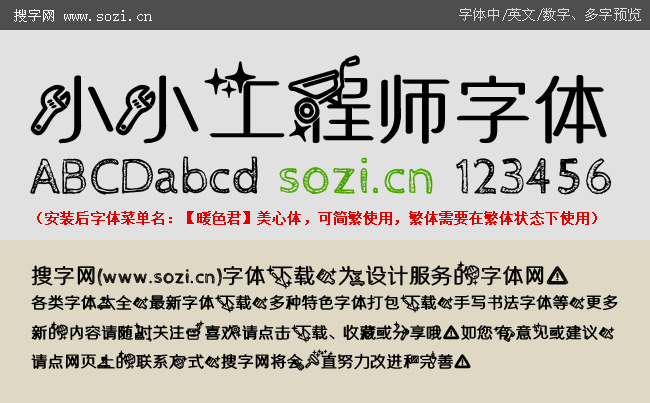
小小工程師字體
搜字網(wǎng)給大家提供一款小小工程師字體手機(jī)中文字體下載。這款手機(jī)字體是以圓體字體為原形,筆畫間嵌入了可愛的卡通工具圖案。在具備圓字體清晰端正的風(fēng)格同時,卡通味也特別濃,是一款非常可愛的卡通字體,特別適合喜歡手機(jī)字體個性一些的朋友在手機(jī)上安裝使用。